網絡世界的內容推陳出新,除了我們會更新造字設計外,還有很多值得大家留意的造字帳户。
喜歡的Follow一下,除了可以表達你的支持,還可以告訴一些名不經傳的造字人,只要堅持,光芒總會被看見的!
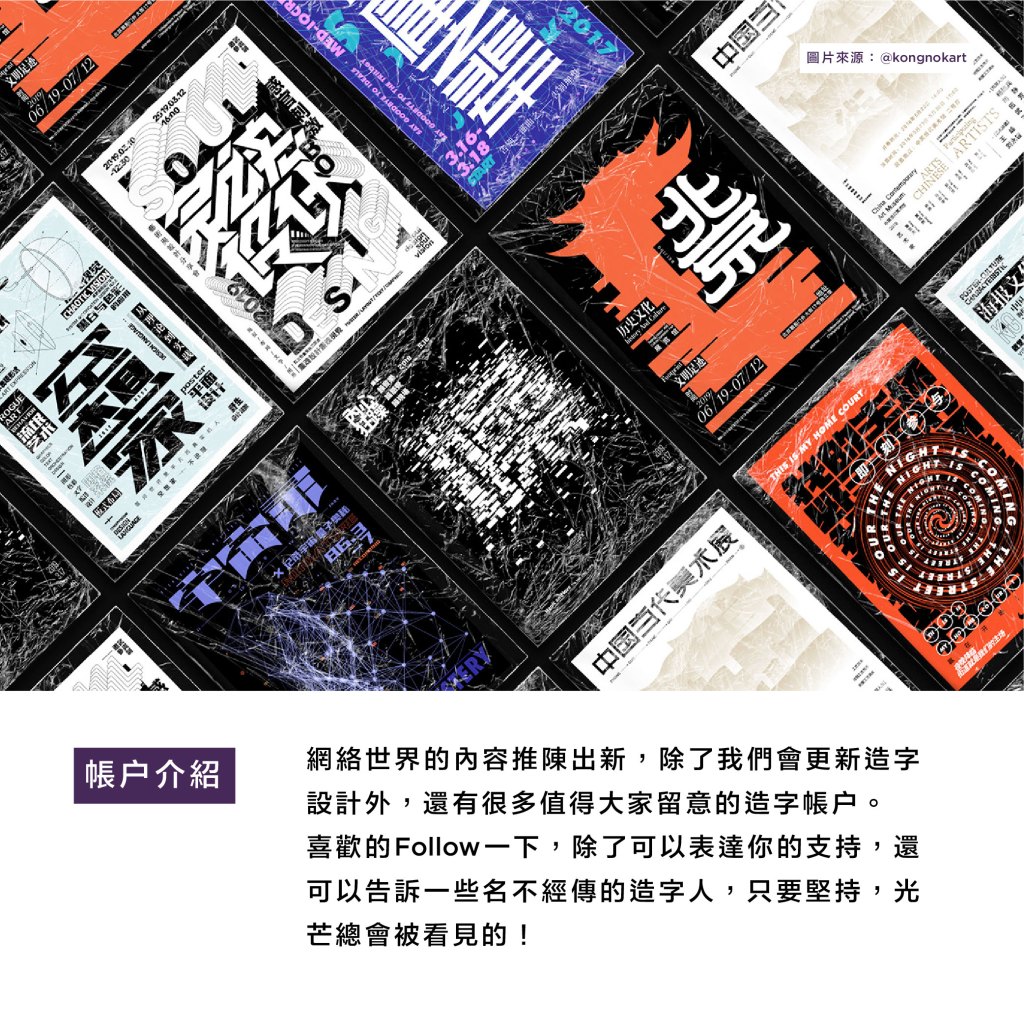
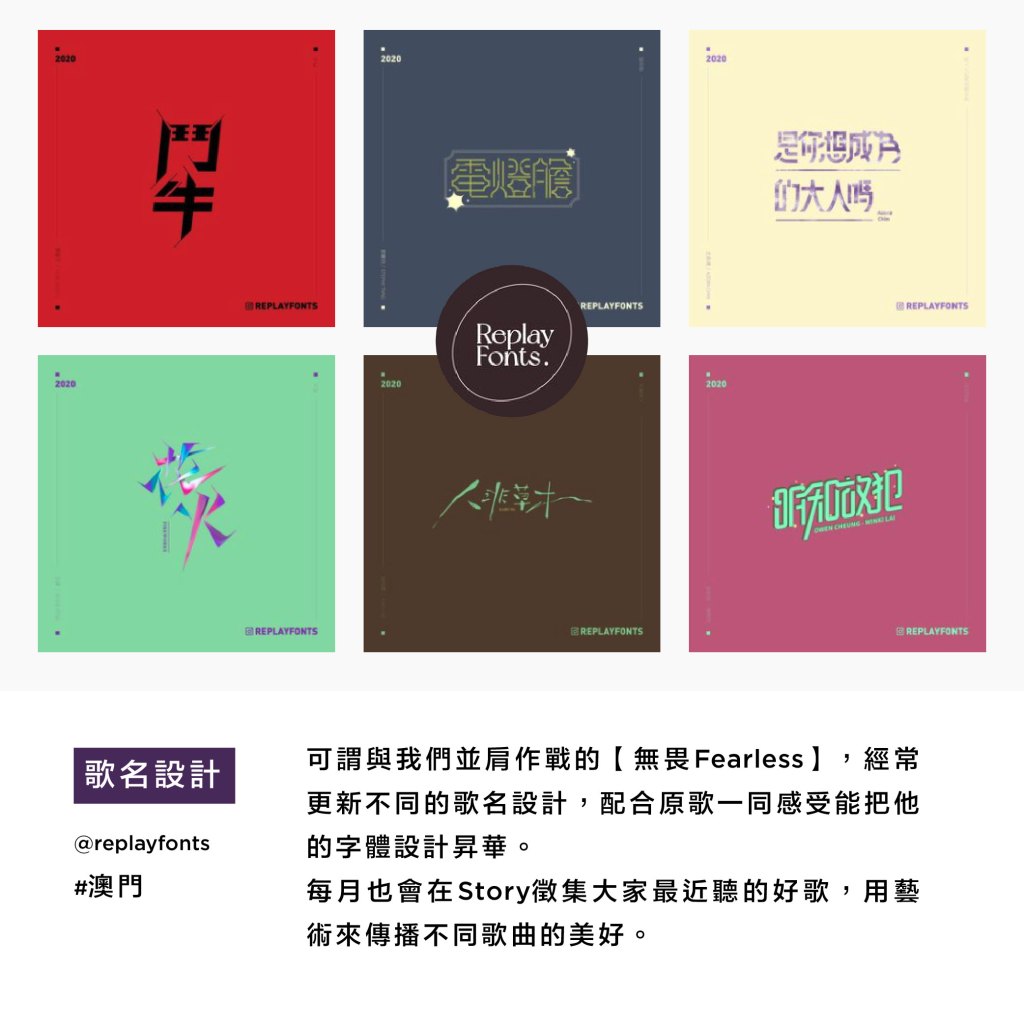
可謂與我們並肩作戰的【無畏Fearless】,經常更新不同的歌名設計,配合原歌一同感受能把他的字體設計昇華。
每月也會在Story徵集大家最近聽的好歌,用藝術來傳播不同歌曲的美好。
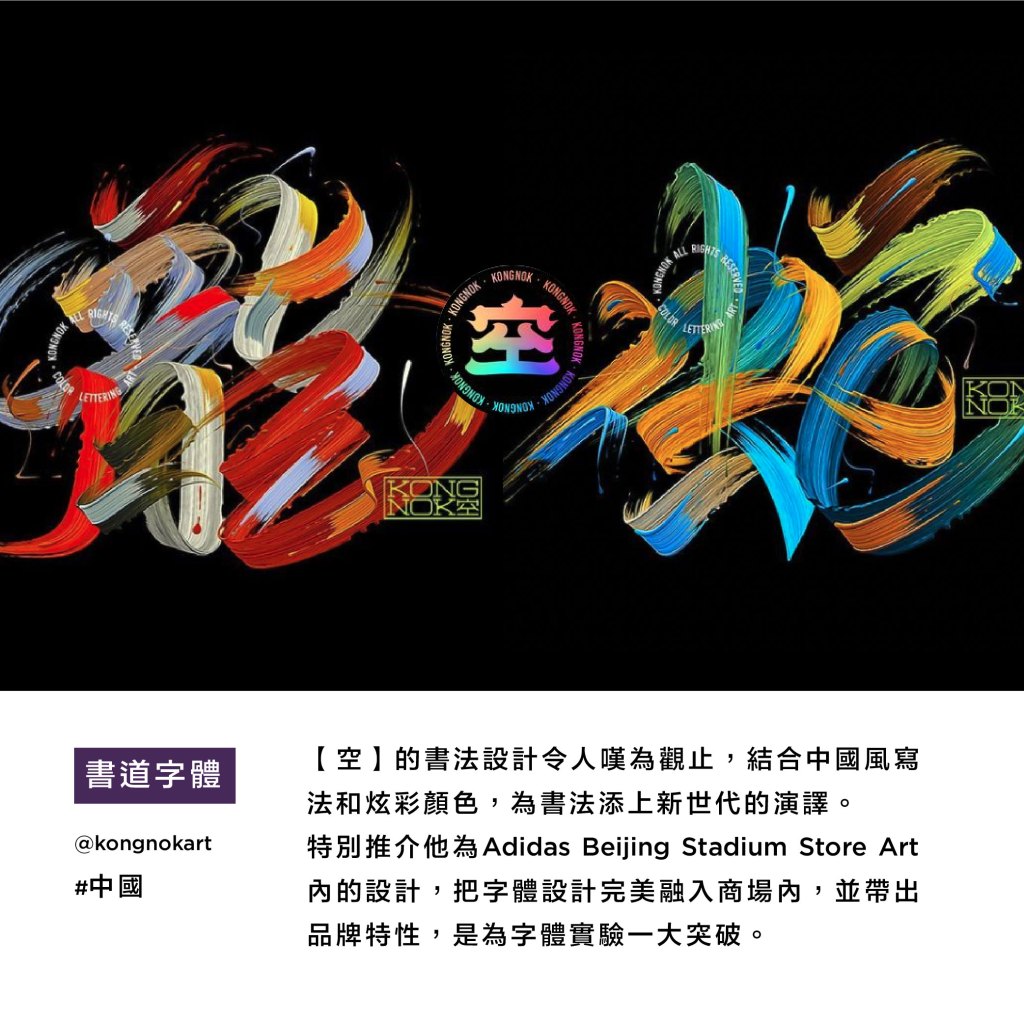
【空】的書法設計令人嘆為觀止,結合中國風寫法和炫彩顏色,為書法添上新世代的演譯。
特別推介他為Adidas Beijing Stadium Store Art 內的設計,把字體設計完美融入商場內,並帶出品牌特性,是為字體實驗一大突破。
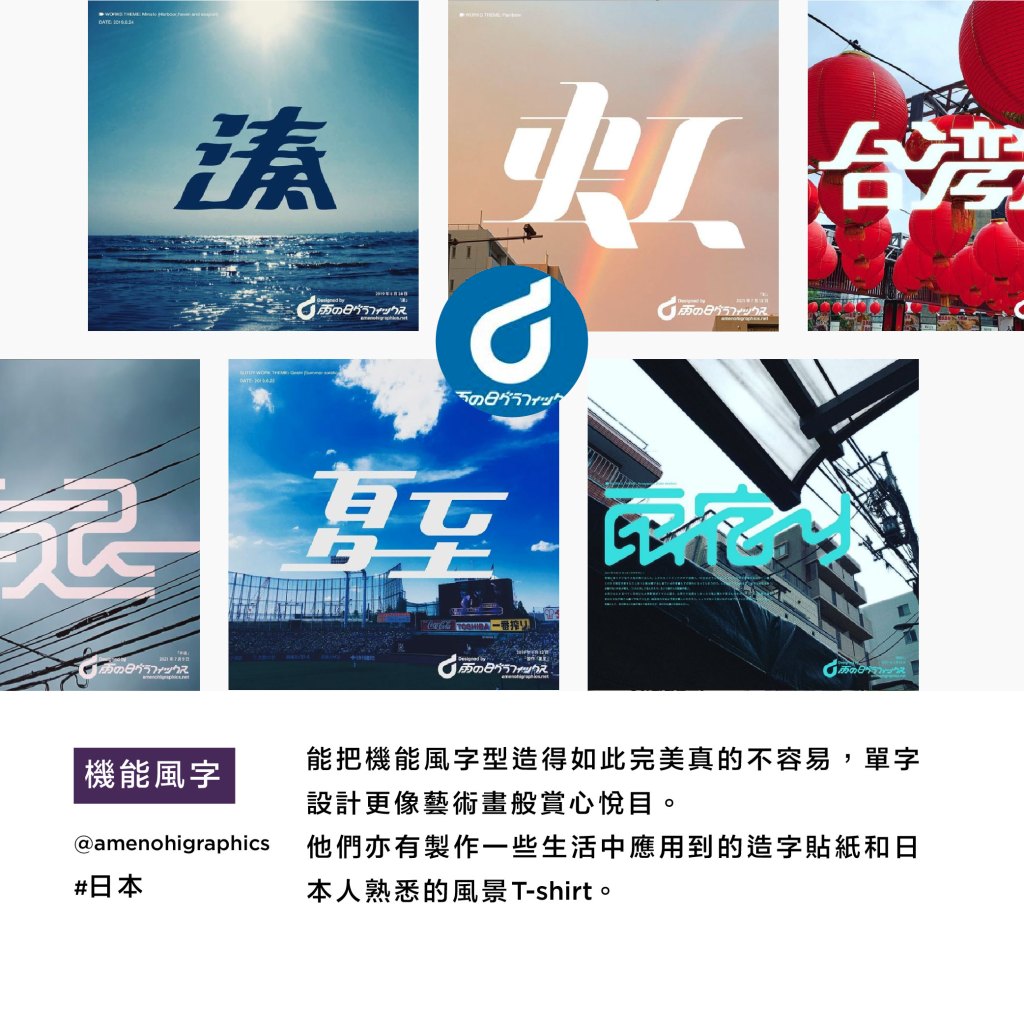
能把機能風字型造得如此完美真的不容易,單字設計更像藝術畫般賞心悅目。
他們亦有製作一些生活中應用到的造字貼紙和日本人熟悉的風景T-shirt。
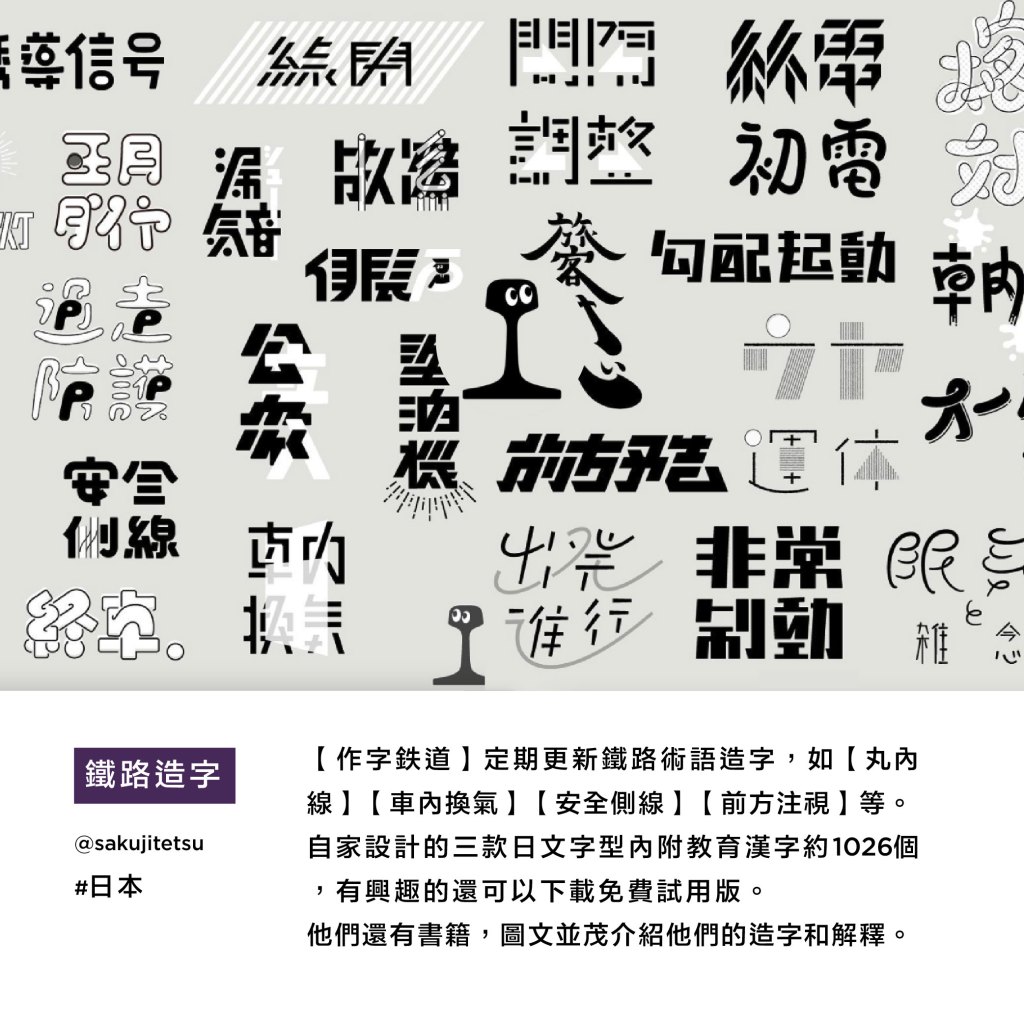
【作字鉄道】定期更新鐵路術語造字,如【丸內線】【車內換氣】【安全側線】【前方注視】等。
自家設計的三款日文字型內附教育漢字約1026個,有興趣的還可以下載免費試用版。
他們還有書籍,圖文並茂介紹他們的造字和解釋。